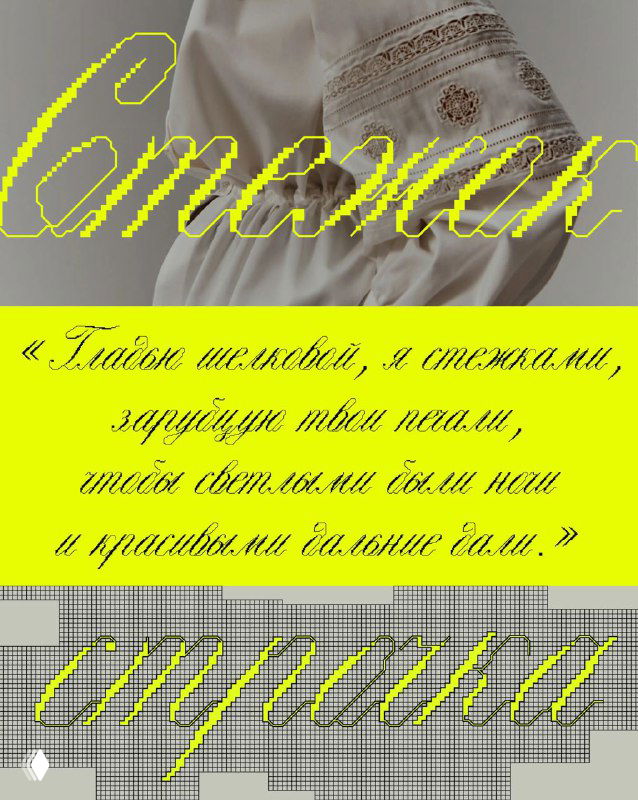
Самобытный декоративный шрифт, вдохновлённый алфавитами из схем по вышиванию. В основу шрифта легли прописи XIX века, которые затем были частично пикселизированы.